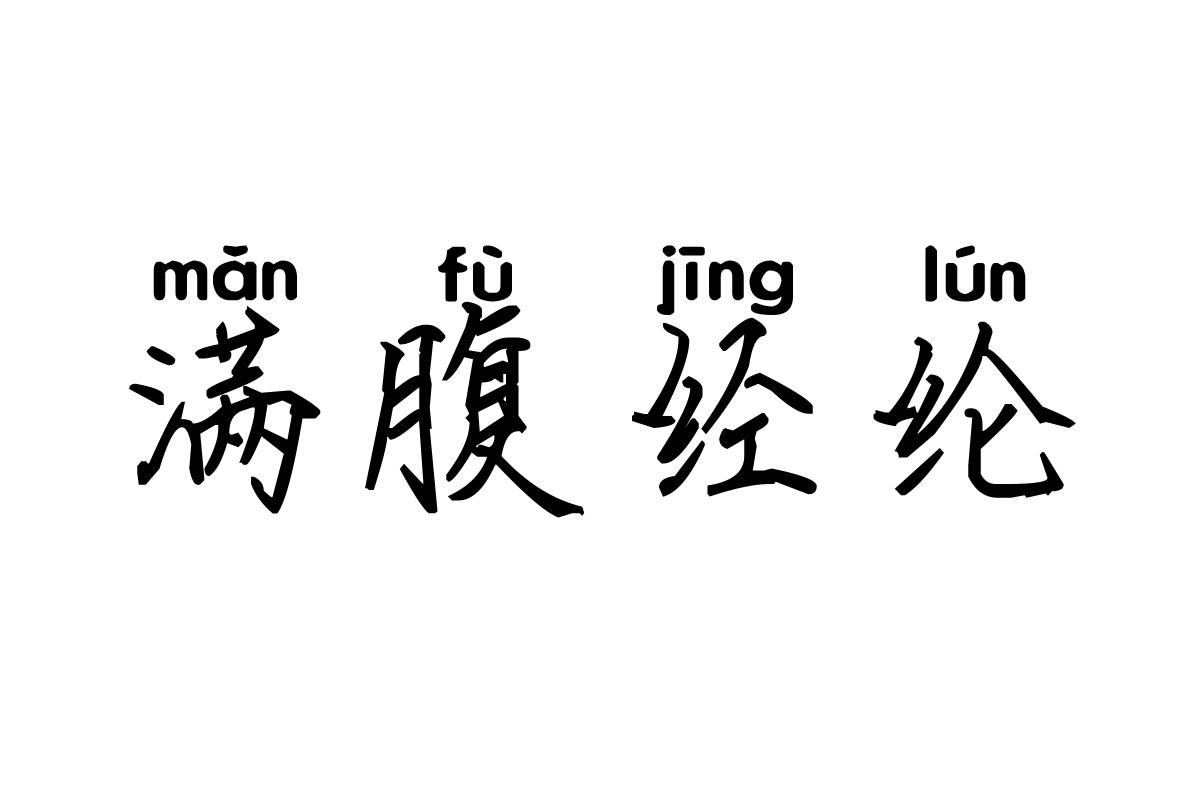
米开水墨丹青拼音体是一款具有中国传统特色的字体,由著名书法家李小龙设计。这款字体结合了水墨画的意境和书法的韵味,线条流畅、笔触有力,既有现代感又不失传统之美。
米开水墨丹青拼音体的字形结构独特,笔画粗细不一,既有楷书的规整,又有行书的自由。这种独特的字形组合使得字体既有美感又有个性,非常适合用于标题、广告、包装等需要突出视觉效果的场合。
此外,米开水墨丹青拼音体还具有一定的可读性,字形大小适中,间距均匀,既适合印刷,也适合手写。这使得这款字体在各种应用场景中都能发挥出良好的效果。